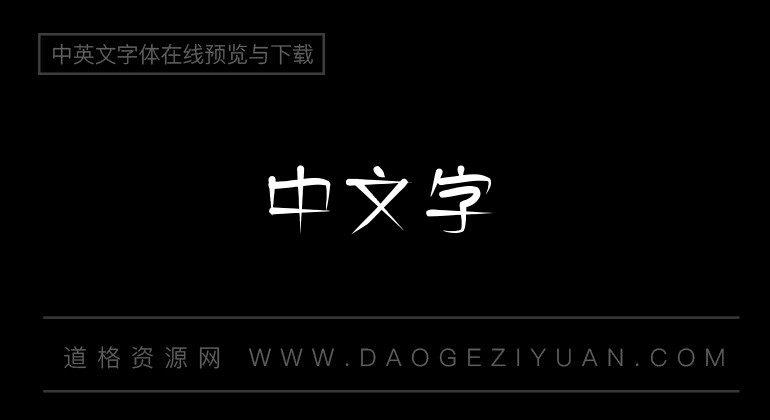
金梅墨笔美工国际码字体是一种汉字字体,它采用了由金梅墨笔设计师精心设计的笔画,结合了传统的汉字绘画技术,融入了国际码技术,使汉字字体更加精致、更加细腻。金梅墨笔美工国际码字体支持多种语言,支持多种字体格式,支持多种编码,能够更好地满足不同语言环境的需求。金梅墨笔美工国际码字体具有良好的可读性和可编辑性,可以更快、更准确地完成文字处理任务。文件名:jinmeimobimeigong.ttf
金梅墨笔美工国际码是一款非常不错的手写艺术字体,具有很好的视觉感,适合于文化类的宣传设计、商业类品牌的广告和产品包装设计以及个性化文字排版等较多场景。